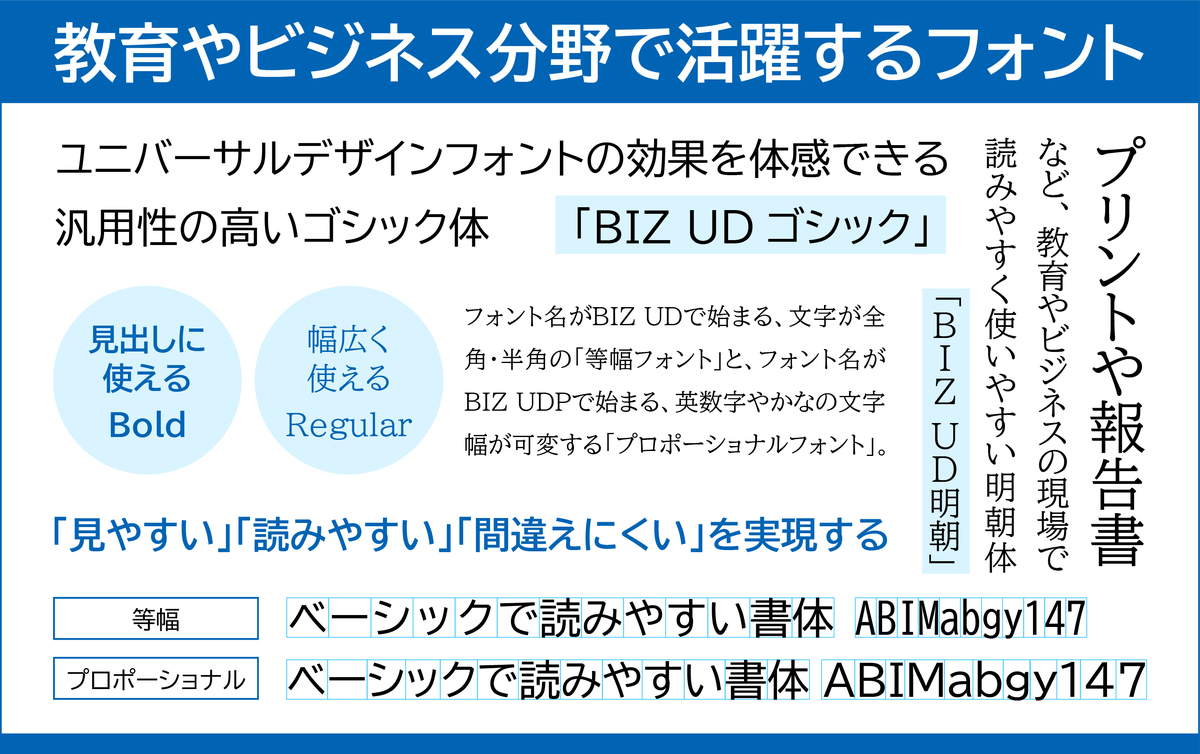
「Google Fonts」へユニバーサルデザインに配慮したUDフォント「BIZ UDフォント」を提供
モリサワは、Googleの提供するフォントサービスライブラリ Google Fonts へ、2022年4月1日にユニバーサルデザインに配慮した「BIZ UDフォント」の提供を開始した。
「BIZ UDフォント」が「Google Fonts」に導入されることで、 Google Workspaceでも利用できるようになることで、データ互換性が高い文書を作成できるようになった。
BIZ UDフォントとは
BIZ UDフォントは、「文字の形がわかりやすい」「文章が読みやすい」「読み間違えにくい」をコンセプトに開発されたユニバーサルデザイン(UD)フォント。
より多くの人にとって読みやすく使いやすいように設計されており、ユーザ評価に基づく読みやすさのエビデンスを取得しており、ICT化が進む教育現場やビジネスでの書類作成をはじめ、正確な情報伝達が必要な場面で使用できる。
2017年からモリサワが展開する、日常的なビジネス文書作成のためのUDフォントソリューション「MORISAWA BIZ+」で初めて提供が開始されたフォントとなる。
「BIZ UDフォント」の「Google Fonts」への提供 概要
▼提供書体
BIZ UDゴシック Regular
BIZ UDPゴシックRegular
BIZ UDゴシック Bold
BIZ UDPゴシック Bold
BIZ UD明朝 Regular
BIZ UDP明朝 Regular
BIZ UD明朝 Bold(2022年11月以降提供開始予定)
BIZ UDP明朝 Bold (2022年11月以降提供開始予定)
▼既存フォントとの互換性について
TrueType版については、モリサワの「MORISAWA BIZ+」およびMicrosoft Windows 10(October 2018 Update以降)、Windows 11への採用版に比べ、教育現場での使いやすさを考慮してIPAフォント Ver.003(最新)の全ての文字をカバーするよう4文字(0x3099, 0x2dc, 0x9b1d, 0x29fd7) を追加した上位互換の位置づけとなるが、その他の部分ではほぼ互換のあるかたちでの提供となる。
BIZ UD明朝 Bold、BIZ UDP明朝 Boldについては、ユーザビリティを上げるため、新たにIPAフォントに準拠した文字数で開発しているもので、他で提供されているフォントには含まれない。